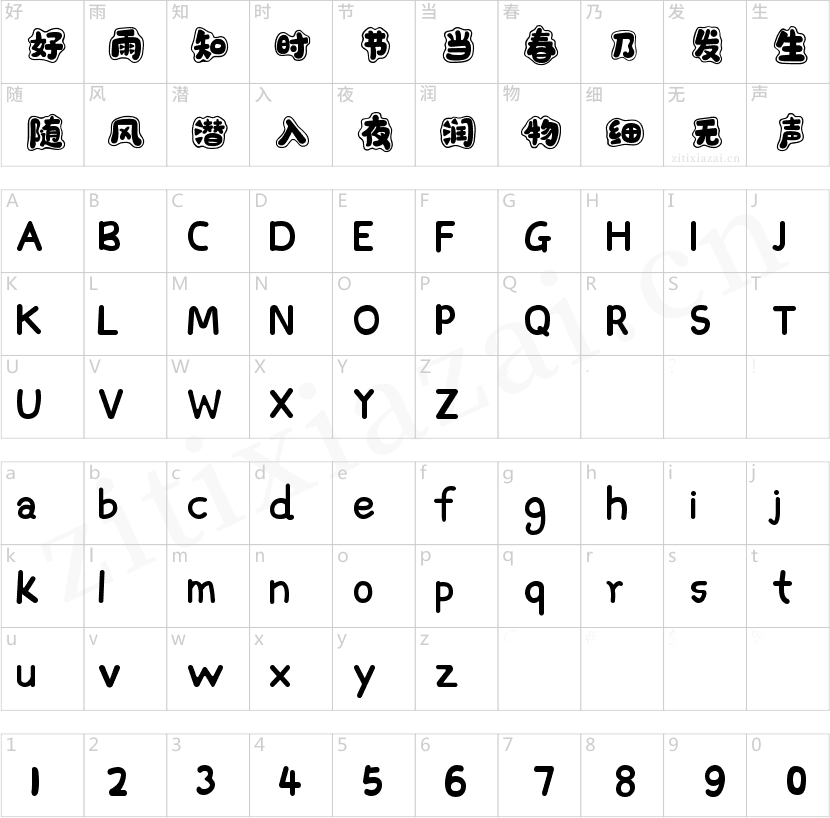
字魂187号-萌趣幸运体
字魂187号-萌趣幸运体,这款字体结构工整、笔画清晰,兼顾美观与易读性,适用于标题、正文、海报、包装、LOGO 等多种场景。字形优雅稳定,风格百搭耐看,适配日常排版与创意设计,让文字呈现更舒适、更具质感。字魂187号-萌趣幸运体一笔一画,皆是细节,以均衡的比例、流畅的线条打造舒适视觉体验,字形端正大气,风格简约现代。无论是商业设计、品牌宣传还是日常排版,都能轻松驾驭,让文字更有格调与力量。字魂187号-萌趣幸运体字体下载。
字魂字体字小魂萌趣幸运体字体是由字魂创意字库设计并生产的一款可商用的字体,被收录于字小魂系列。该字体支持GB-2312标准,包含6763个中文、字母、符号和数字,字体类型偏向创意字体,具有活泼、可爱、圆润的风格,在市面上广泛用于旅游、社交、运动户外等场景。